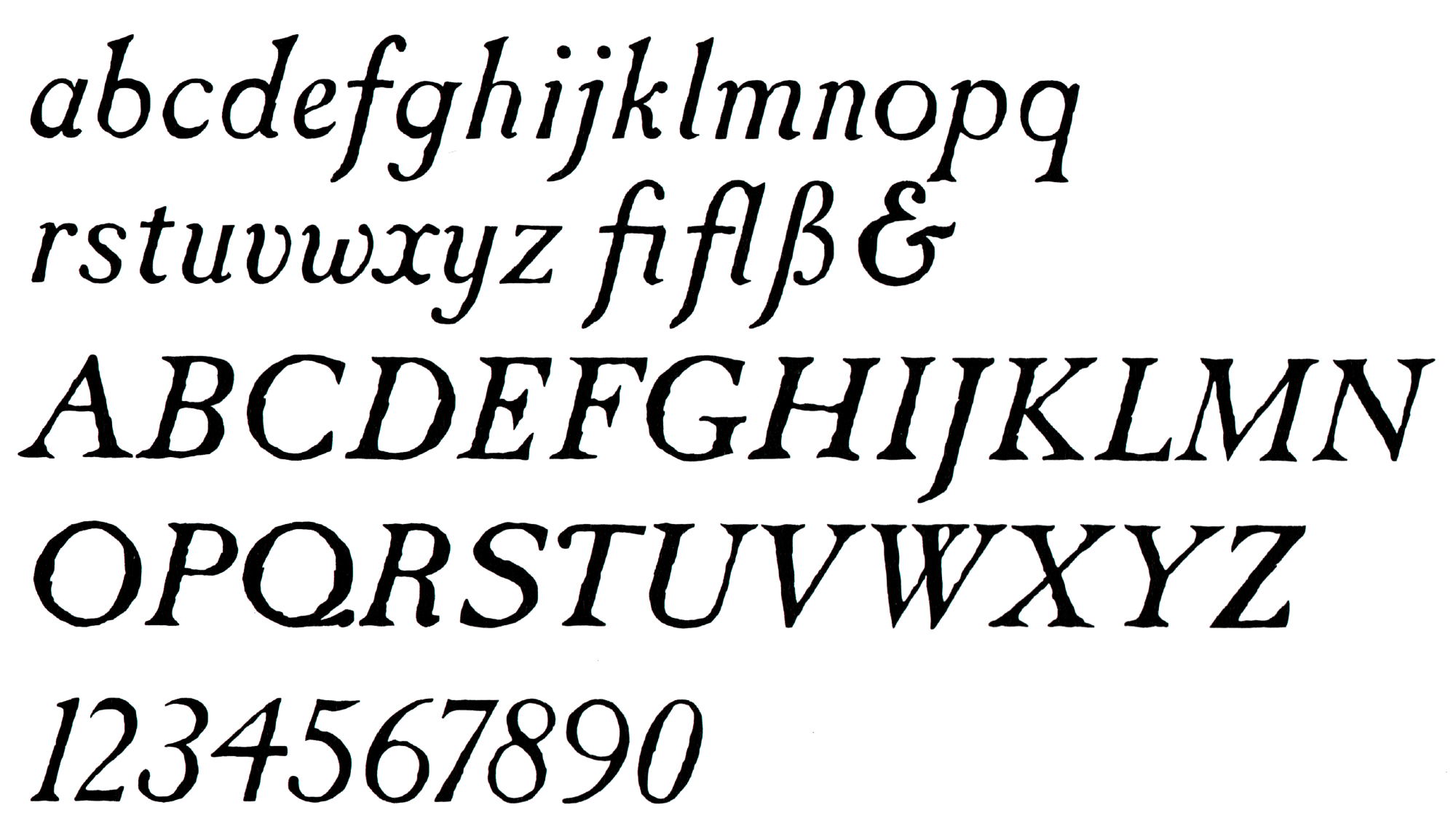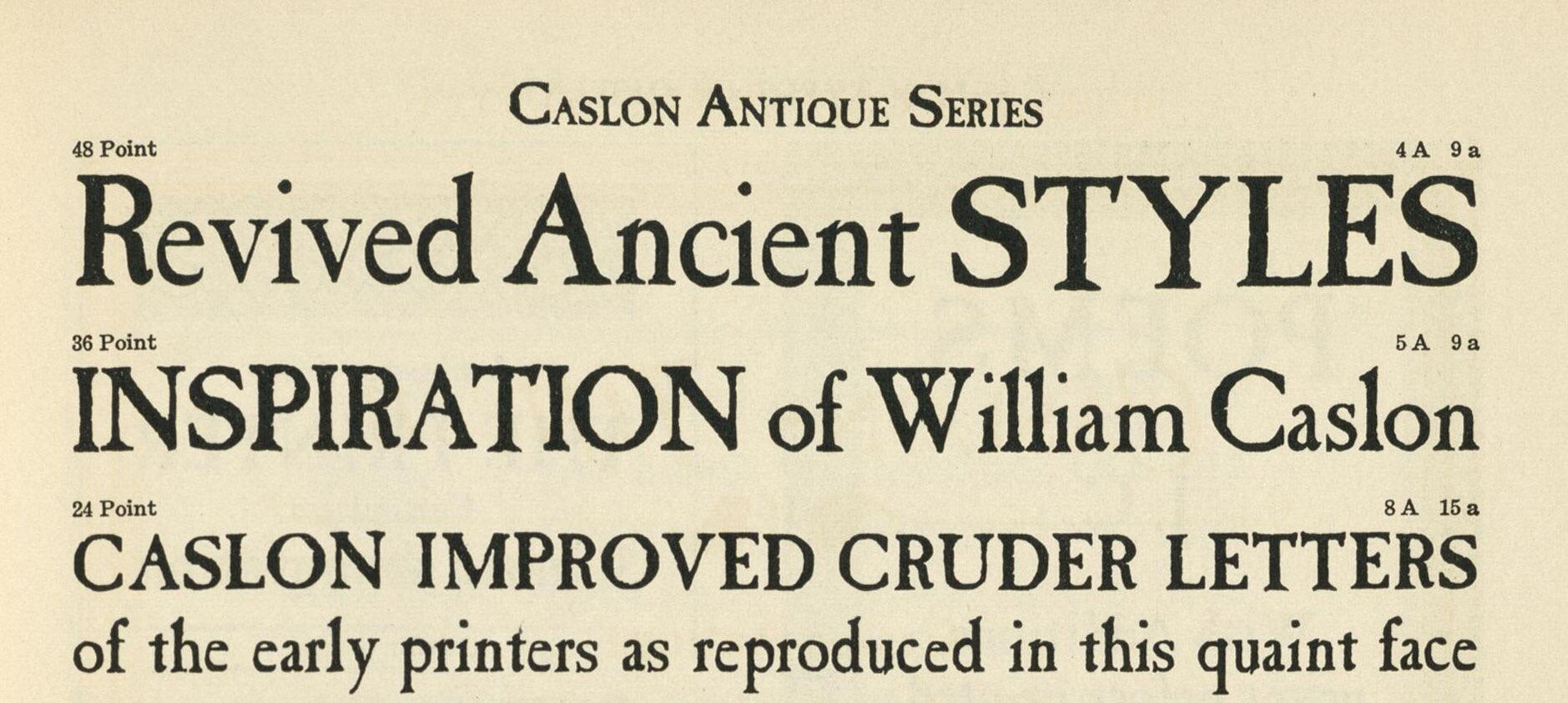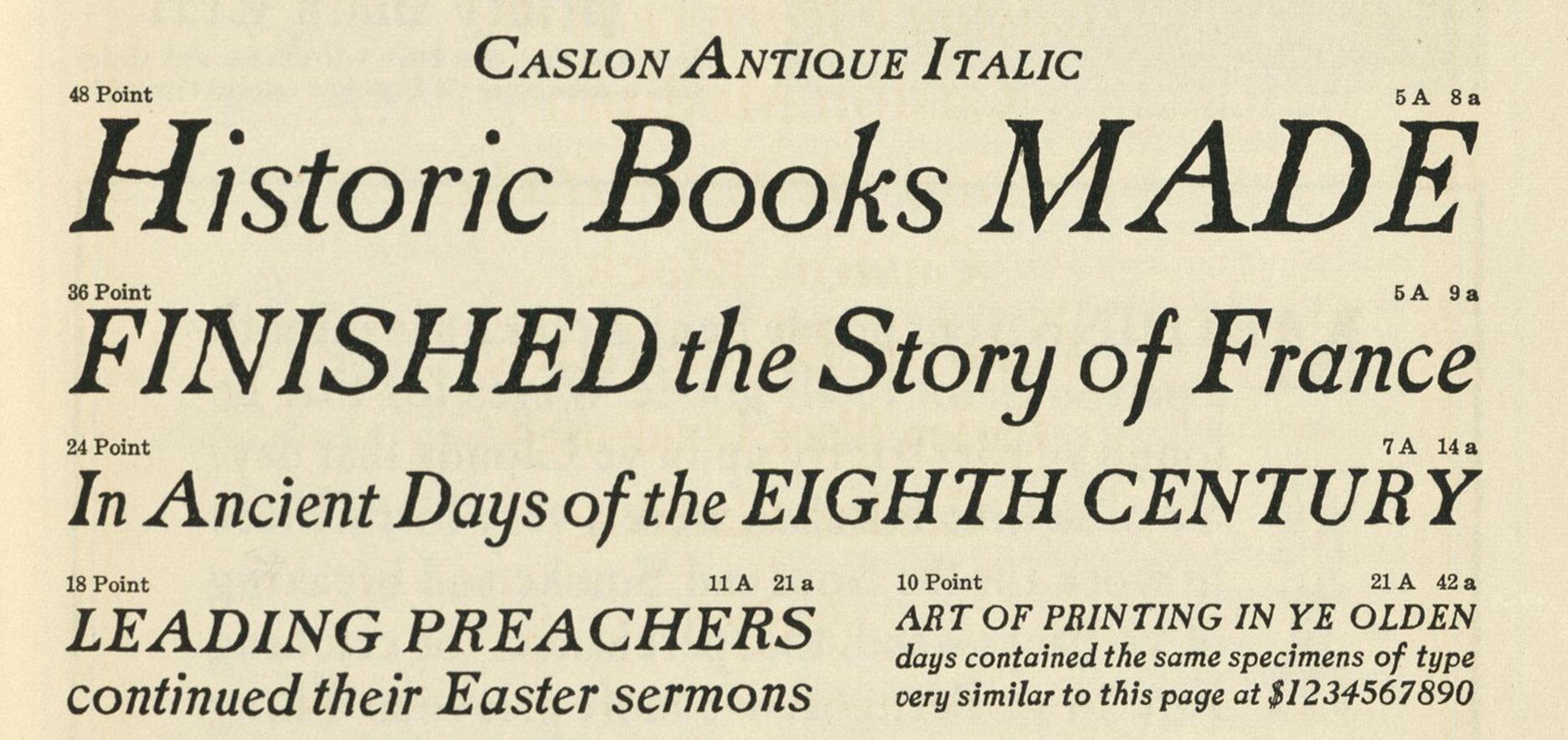
- circa 1896
- Antiqua humanistisch
Die Caslon Antique erschien Ende des 19. Jahrhunderts bei der US-amerikanischen Gießerei Barnhart Brothers & Spindler, zunächst noch unter dem Namen Fifteenth Century. Erhältlich waren ein aufrechter und ein kursiver Schnitt mit betont rauer Umrisslinie.
Die Schrift wurde später auch in den Foto- und Digitalsatz übernommen und ist heute von verschiedenen Anbietern erhältlich, meist jedoch nur mit dem aufrechten Schnitt.